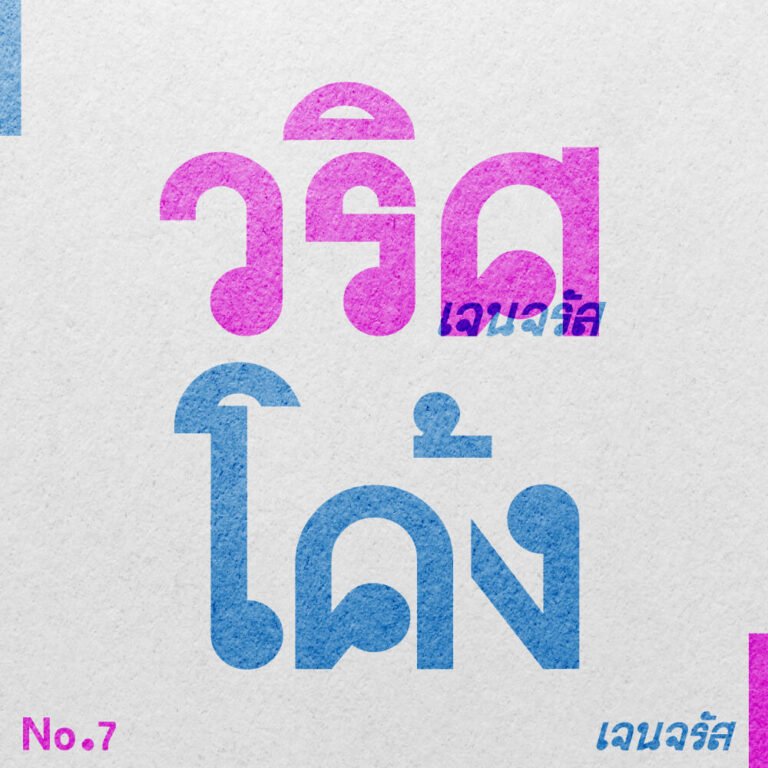
เจนจรัส วริศโค้ง (Jenjrus VrisKhong)
ฟอนต์เจนจรัส วริศโค้ง เป็นฟอนต์ตัวหนา ซึ่งดัดแปลงจากเวอร์ชันปกติหลังคาเหลี่ยม เป็นหลังคาโค้งๆ อ่านง่าย เรียบร้อย เหมาะกับเป็นหัวข้อหรือทำป้ายและสื่อโฆษณาต่างๆ
ฟอนต์นี้เป็นผลงาน ชุดที่ 7 ของคุณพ่อ อายุ 77 ปี ที่รักการออกแบบฟอนต์เป็นงานอดิเรกครับ
ออกแบบและผลิตโดย : ชาญวุฒิ เจนจรัสสกุล